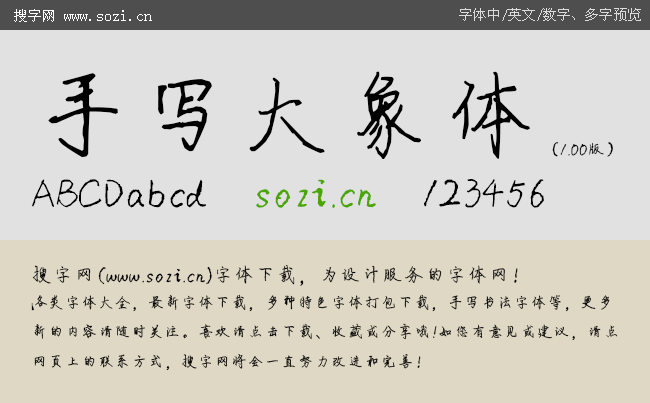
手寫大象體
搜字網(wǎng)提供一款手寫大象體中文書法字體下載,手寫大象體是一款手寫風(fēng)格的鋼筆書法字體,字體書寫流暢,字形大方,整體效果十分出色,適合應(yīng)用于廣告設(shè)計(jì)、名片設(shè)計(jì)、包裝印刷、產(chǎn)品設(shè)計(jì)等應(yīng)用。